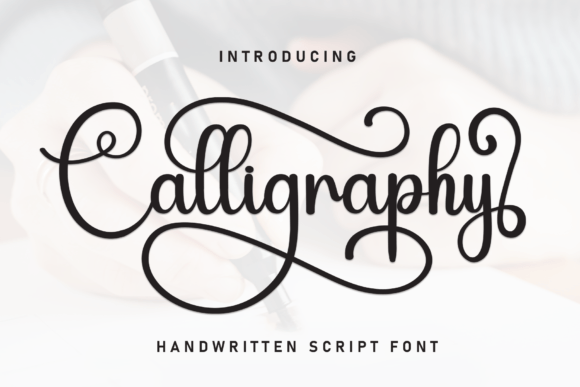
Calligraphy
Calligraphyのような高品質の素材をお探しの場合、このプレミアムパッケージはクリエイティブなプロジェクトに素晴らしい選択です。
POD(オンデマンド印刷)製品、結婚式の招待状、またはソーシャルメディアのグラフィックを作成している場合でも、Calligraphyは理想的です。